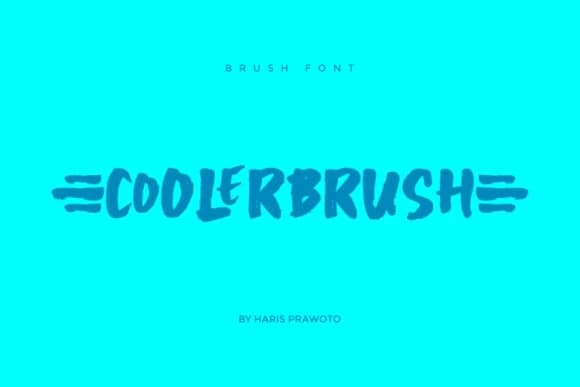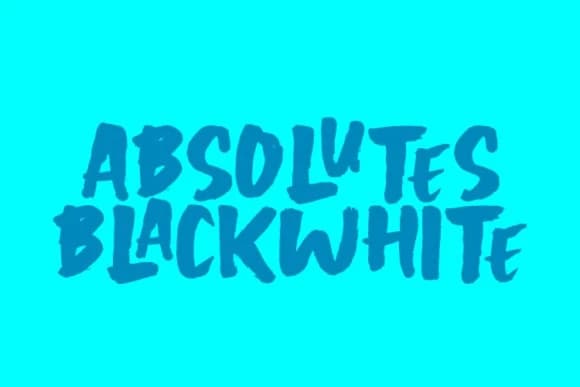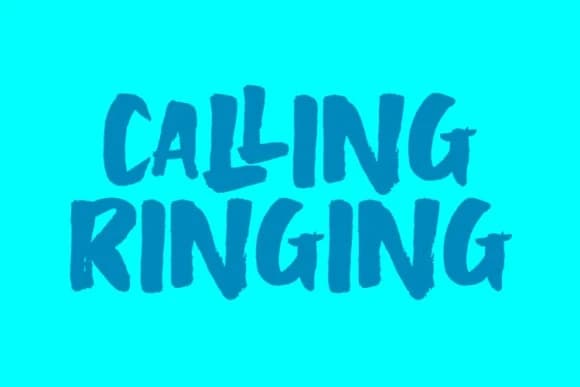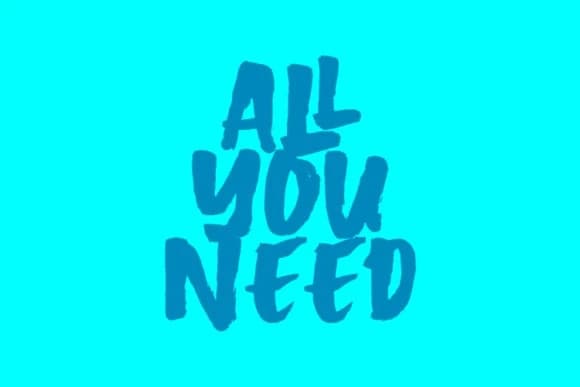
Coolerbrush Font
Coolerbrush Font, benzersiz, kalın karakterli bir gösterim yazı tipidir. Basit ve biraz tuhaf stiliyle bu yazı tipi pek çok tasarım türüne uyum sağlar. En yaratıcı fikirlerinizin yanına ekleyin ve bunun onları nasıl öne çıkardığını görün!
Coolerbrush Font benzersiz, iri karakterlere sahip bir gösteri yazı tipidir. Sade ve biraz garip bir tarzı bu yazı tipinin geniş tasarımlara uyum sağlamasına olanak tanır. En yaratıcı fikirlerinize ekleyin ve bunun onları nasıl öne çıkardığını fark edin!